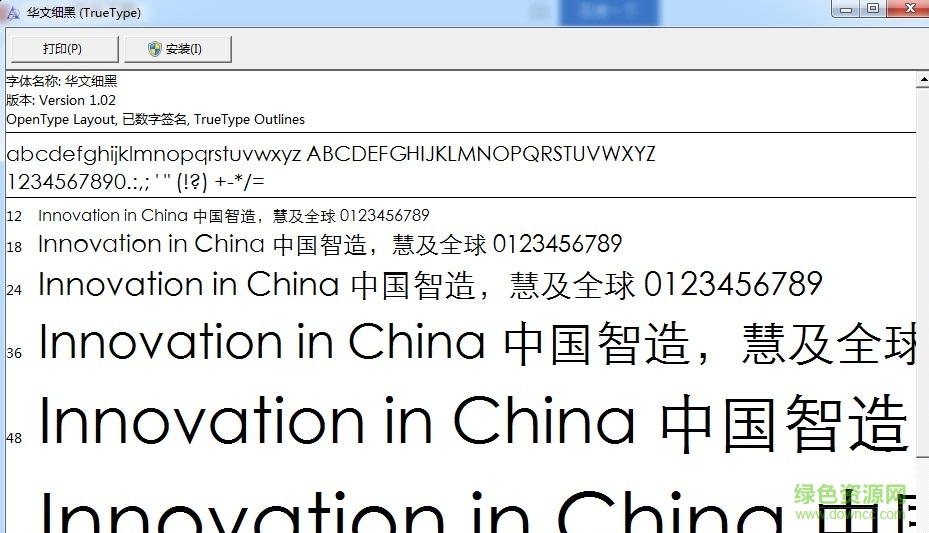
stxihei 華文細(xì)黑是一款非常經(jīng)典的字體哦,這款字體的使用范圍也是非常廣泛,標(biāo)題和文字全都很實(shí)用,用來設(shè)計(jì)海報(bào)、期刊等非常合適!有需要的就來綠色資源網(wǎng)下載吧!
stxihei字體介紹
華文細(xì)黑,是由中國常州華文印刷新技術(shù)有限公司(SinoType)制作并持有版權(quán)的一種TrueType電腦字體。在無中文的環(huán)境下顯示的名稱為STHeiti Light或STXihei,它屬于華文黑體系列字體之一。在設(shè)計(jì)上,它屬于黑體或無襯線體。